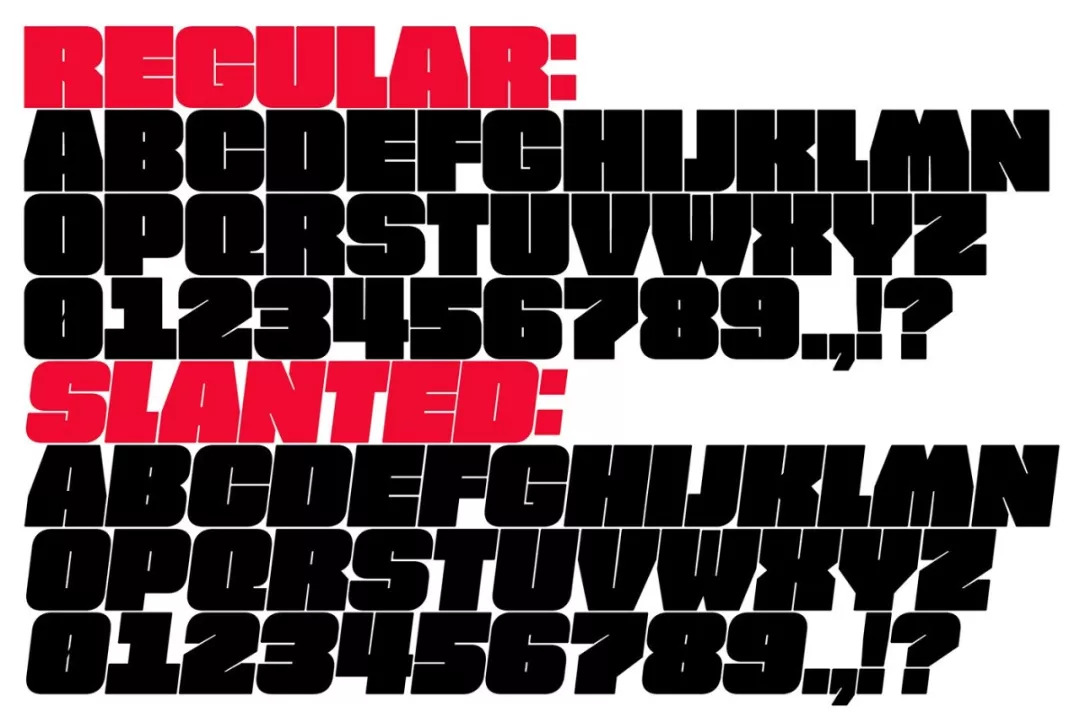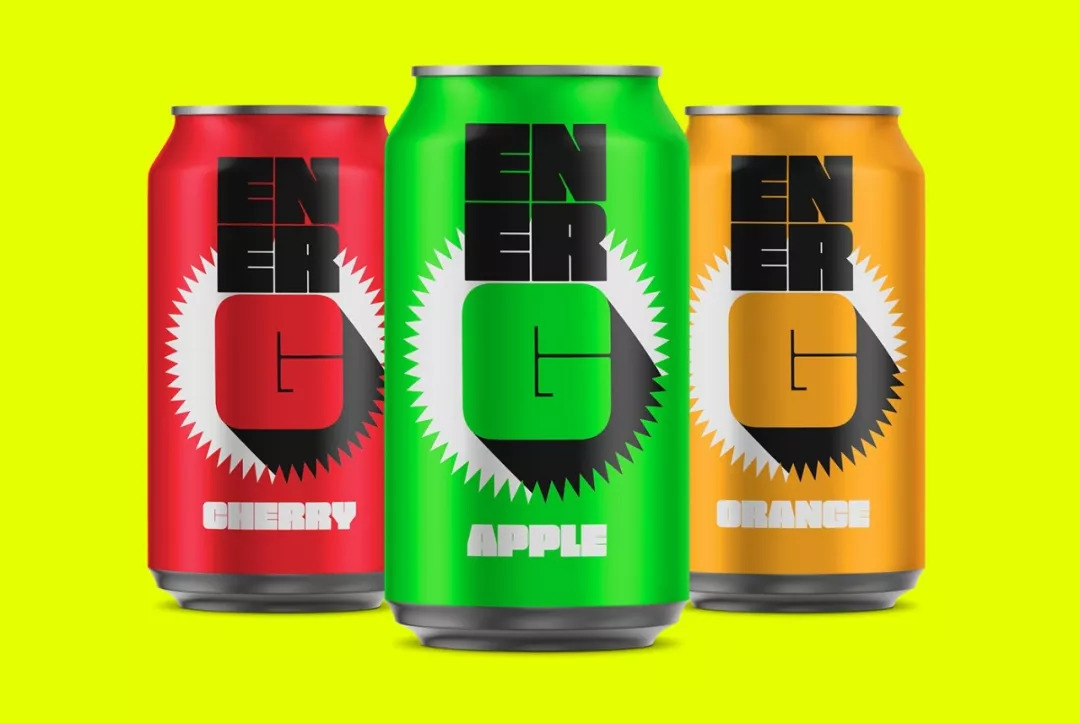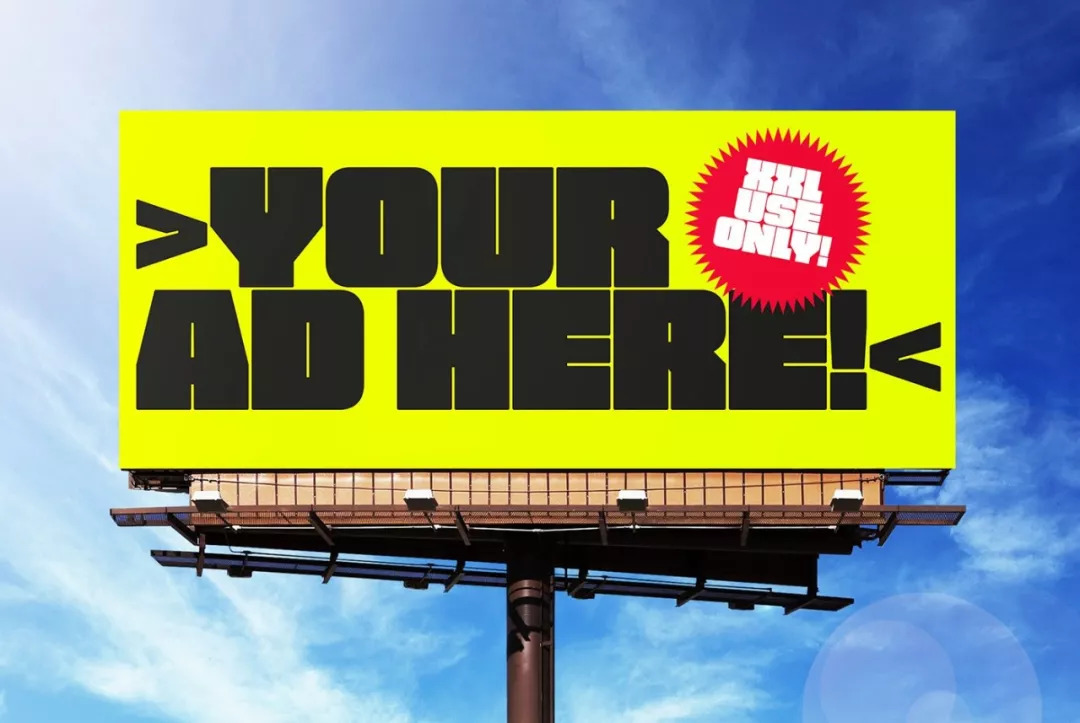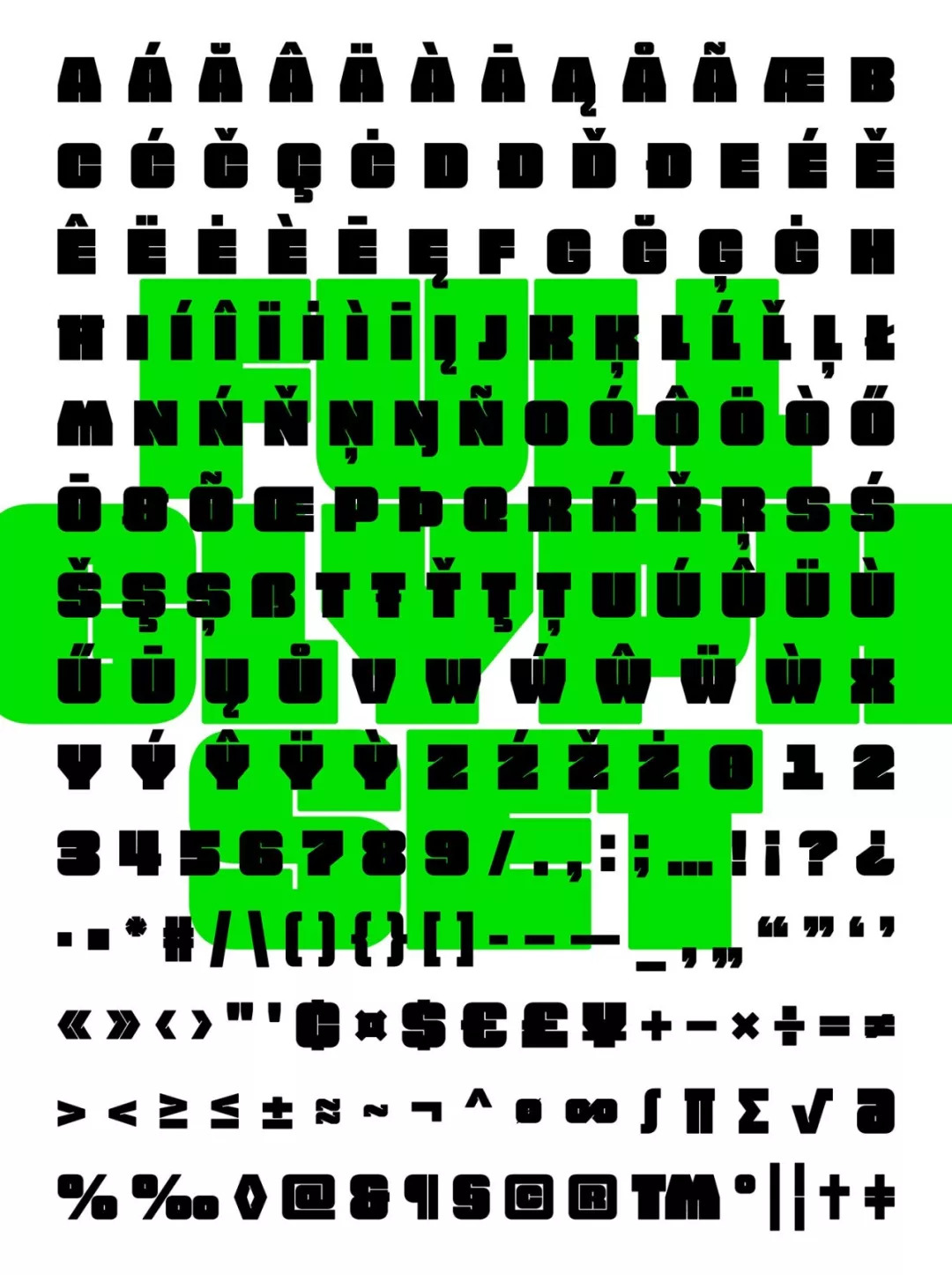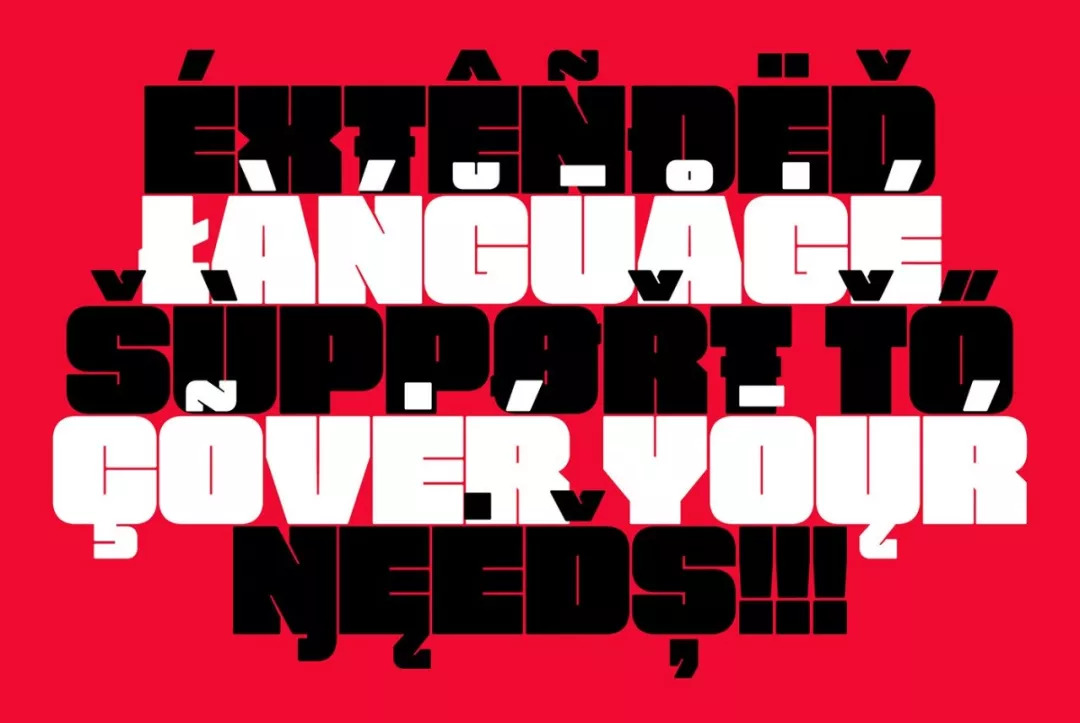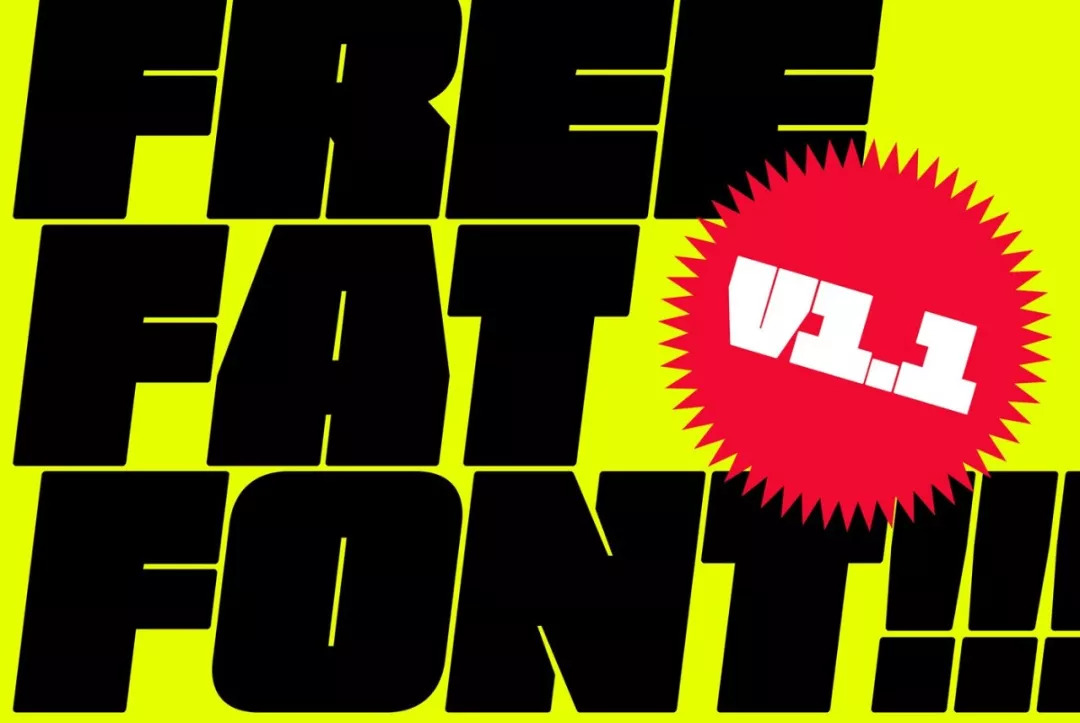
Free Fat Font,这字体够醒目,绝对粗,还是免费商用的
Free Fat Font由Thom Niessink创作,
正是您所期望的,
它足够胖,而且是免~费~商~用的。
这款字体具有极粗的字重和许多独特的字符,仔细观察看看,这些字符非常有趣。
设计画面上使用如此“粗壮”的字体,甲方霸霸再也不会说字体不够醒目了。
很明显,这款字适用范围很广泛,如大型标题,户外广告宣传,醒目的标签,包装以及任何需要大量冲击视觉冲击力的场景。
它还具有多语言字符,进一步提高了这款字体的可用性。